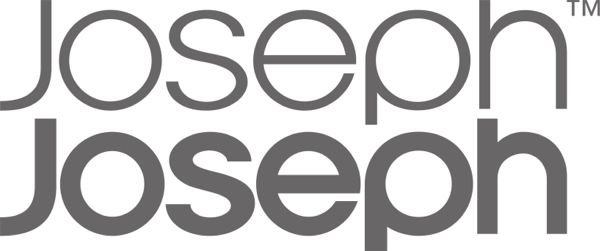
Ich bin auf der Suche nach der Schriftart des "joseph joseph" - Logo...
Da werden wohl Avant Garde und Arial (?, fürs s) Pate gestanden haben.
Eventuell handelt es sich auch um die Chalet New York und die Chalet Paris, bei der die Buchstaben der jeweiligen Schnitte miteinander kombiniert und anschließend modifiziert (Ober- und Unterlänge gekürzt) wurden.